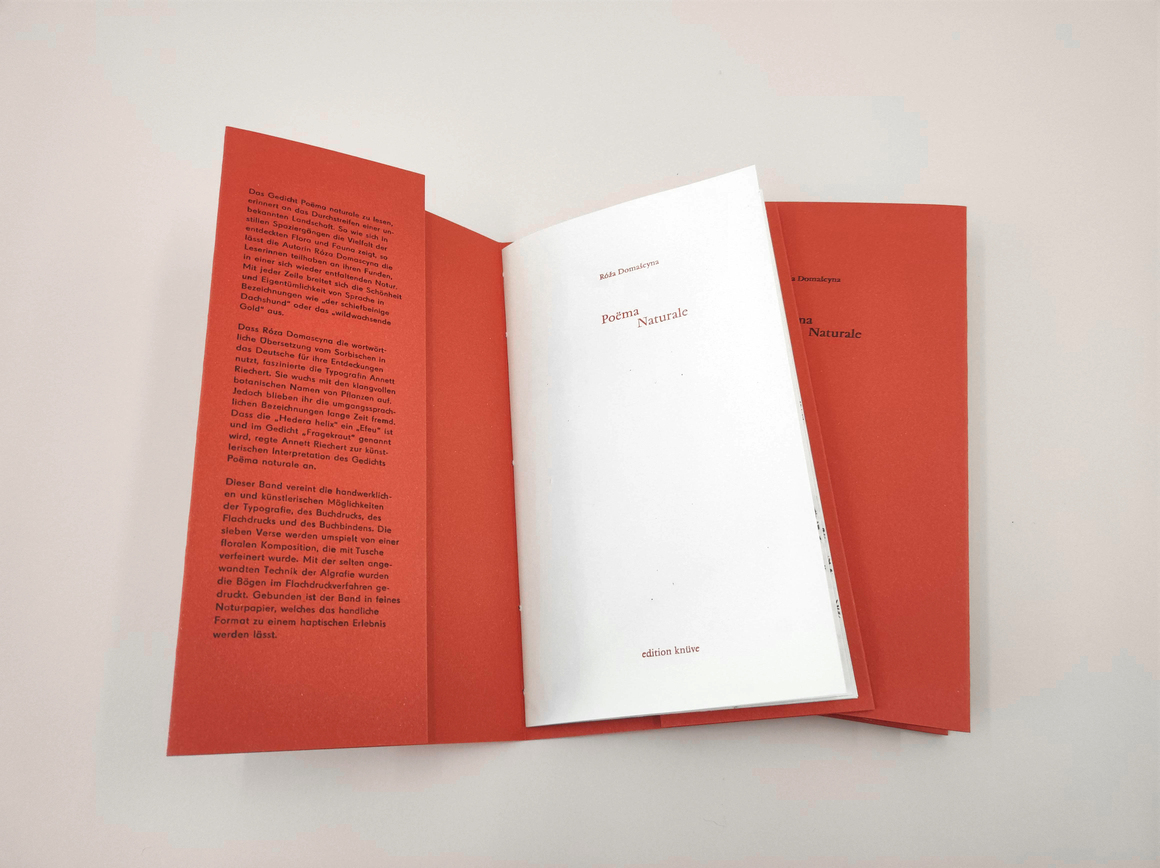
Buch: Poëma Naturale in der Edition Knüve erschienen
Poëma Naturale – meine buchkünstlerische Auseinandersetzung mit dem Gedicht der sorbischen Autorin Róža Domašcyna
In dem zwölfseitigen Band mit Cover findet die künstlerische Auseinandersetzung mit den Mitteln von Sprache, Typografie und der traditionellen Handwerkskunst des Buch- und Hochdrucks statt. Das Gedicht Poëma Naturale von Róža Domašcyna wurde in inszenierender Typografie gestaltet. In der aufwendigen Technik der Algrafie entstand der sich durch das Buch ziehende florale Druck. Durch diese Verbindung von Sprache, Typografie und floralen Materialdrucken entstand das handwerklich gefertigte Buch, welches das Interesse für die Pflege und Förderung der sorbischen Sprache und Kultur als Ausdruck der Identität des sorbischen Volkes sichtbar macht. Die hochwertige und handgebundene Ausgabe nutzt traditionelle Handwerkstechniken, unterstützt damit die Bewahrung der sorbischen Identität und stärkt die Präsentation sorbischer Kunst und Kultur auf regionaler, nationaler und internationaler Ebene.
Das für den Lyrikband verwendete Gedicht beschäftigt sich mit einer Besonderheit von Sprache und Umgangssprache. Die Begriffe von Flora und Fauna unterscheiden sich je nach Sprachraum, ja auch nach Region oder Dialekt. Diese in eine andere Sprache zu übersetzen, heißt sich der Begriffe der anderen Sprache zu bedienen. Róža Domašcyna stellt aber die rein sprachlich übertragenen Begriffe den Übersetzungen gegenüber. Aus dieser Semantik entsteht eine Spannung, die zur Interpretation und Auseinandersetzung einlädt und somit den Raum für eine Auseinandersetzung mit der sorbischen Sprache einlädt. Das handwerklich gestaltete Buch verbindet so die kulturelle Tradition, die sprachwissenschaftliche Analyse und die künstlerische Umsetzung zu einem einzigartigen Projekt.
Das Gedicht Poëma Naturale wurde von Róža Domašcyna geschrieben und reiht sich ein in ihre vielfältiges lyrisches Œuvre. Das Gedicht Poëma Naturale wurde 2006 in dem Band Stimmfaden im Verlag Das Wunderhorn veröffentlicht. Róža Domašcyna arbeitete als Übersetzerin und hat somit einen besonderen Blick auf die Feinheiten von Sprache. Dies sollte im Projekt als inhaltliche Schwerpunkte mittels inszenierender Typografie und traditioneller Handwerkskunst in einen Lyrikband sichtbar gemacht werden und zugleich als kulturelle Repräsentation der sorbischen Literatur im nationalen und internationalen Kontext wirken. So zurückhaltend wie die Dichterin in ihrem Gedicht von dem Wiedererwachen der Natur nach einem Feuer schreibt und sorbische Namen mit den deutschen verwebt, sollte auch die inszenierende Typografie sich einfügen und ein weiteres Element auf der Seite eines Verses werden. Die floralen Drucken sollen sich, zart begonnen, in der Wildheit der Mitte bis zum Schlussbild entfalten und so von der Kraft der Natur, dem immer wieder Aufkeimen und Fortpflanzen Zeugnis ablegen. Dies als Symbol für den Fortbestand bedrohter Sprachen, für die Schönheit und Bedeutung des Sorbischen. Mittels der scheinbar gebrochenen Sätze ab Vers zwei wird auf die Vernetzung und Durchdringung der sorbischen Lebenswelten eingegangen. Nicht der Zeilendurchschuß wurde verwendet, sondern die gebrochenen Zeilen hängen aneinander, wie die Übersetzung des sorbischen Begriffs, in all seiner Poetik, gemeinsam mit dem deutschen und dem lateinischen semantisch vernetzt ist.
Mit dem Fokus auf die Semantik der Bezeichnungen im Gedicht wurde ein besonderer Wert auf den Dialog mit dem Material, mittels Pflanzendrucks, gelegt. Ein Ziel war, die aus der Natur entnommenen Pflanzen durch einen direkten Abdruck sichtbar und in ihrer Vielfalt und Authentizität erfahrbar werden zu lassen. Dieses Vorhaben konnte mit der Flachdrucktechnik, der Algrafie, umgesetzt werden. Dafür waren jedoch Vorarbeiten notwendig, wie das Identifizieren von entsprechendem floralen Materialien, das Entnehmen aus der Natur und Waschen, sowie das Schneiden mittels eines Skalpells. Die benötigten Pflanzen wurden für zwei Stunden zum Antrocknen gepresst, sie behielten durch diese kurze Phase ihre Vitalität und konnten zum Druck verwendet werden. Im ersten Druckgang wurde das Pflanzenmaterial nahtlos aufgebracht, wie es beim Blättern im Buch zu sehen sein würde. Vor dem Belichten der Algrafieplatte wurde der Druckbogen ausgeschossen, die Vorlagen für Schön- und Wiederdruck angelegt. Nach dem fotomechanischen Belichten der Algrafieplatte wurde diese aktiviert und fand im floralen Druck ihre Verwendung. Diese drei Phasen gleichen den Metamorphosen der Pflanzenwelt im Jahresverlauf oder wie im Gedicht von Róža Domašcyna, nach einer (Feuer)-Apokalypse. Das Abbild der Pflanzen in den Phasen meiner Arbeit und die Pflanzen in der Natur sind regelmäßigen Veränderungen unterworfen, verändern sich, vom Hummus ausgehend, der die Samen nährt bis zur fruchtenden, ausgewachsenen Pflanze, bleiben doch immer sie selbst.
Ein weiteres Ziel war die Durchdringung des Textes und der floralen Gestaltung mittels einer inszenierenden Typografie in der Tradition der vergangenen zweihundert Jahre, begonnen mit Mallarmé, Ende des 19. Jahrhunderts, bis zur die Visuellen Poesie. Der Bedeutungsrahmen einiger im Gedicht verwendeter Pflanzen sollte um die lateinischen Begriffe dieser erweitert werden, jedoch wurde auch auf das Spiel der Dichterin eingegangen, so streuen sich Bruchstücke auf den Seiten des Lyrikbands und nur auf der letzten Seite, gleich einem Schlussakkord, türmt sich in drei Zeilen gestapelt der Rosmarin. Die Funktion dieser inszenierenden Typografie liegt in der Einladung zum Dialog, zur Auseinandersetzung mit Sprache und mit Fremdheit. In der bewußten Verwendung von Wortteilen liegt die Aufforderung sich tiefgründig mit der Verwandlung von Begriffen auseinanderzusetzen. Die poetischen Übersetzungen von Róža Domašcyna stehen dabei als Bedeutungsebene, weisen auf ihren Ursprung, die sorbische Sprache, hin. So wurde der Semantik des Gedichts neben den sorbischen Übersetzungen und den deutschen Begriffen mit den lateinischen Bezeichnungen eine weitere Einheit hinzugefügt (und es wäre ein leichtes, dieses System auf alle Sprachen der Welt, soweit die Pflanzen als solche bekannt sind, zu erweitern).
Handwerk: Handsatz, Floraler Druck, Flachdruck (Algrafie), Buchdruck, Handbindung
Fonts: Bleisatz: Vendôme, François Ganeau (1951) und Super Grotesk.